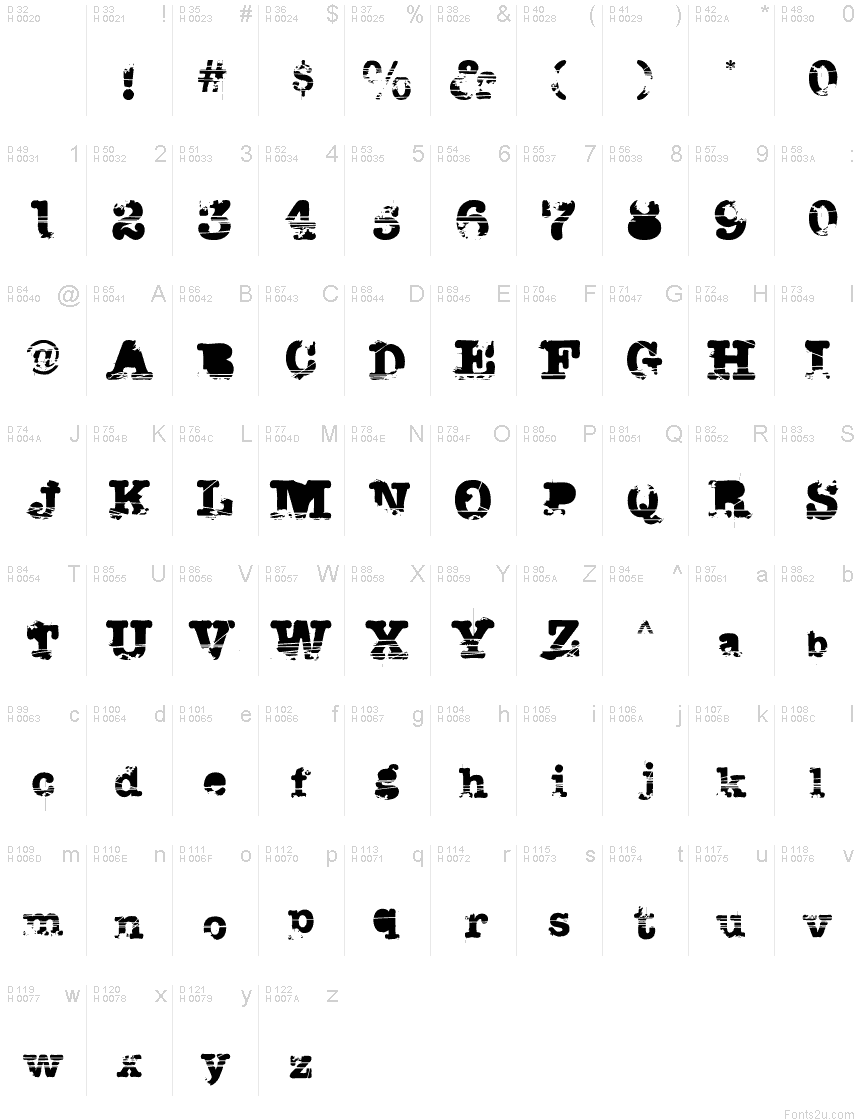
Sacrafical è un font display gratuito dallo stile eroso, che richiama l'estetica usurata dei vecchi caratteri in legno. Con le sue grazie arrotondate e massicce e i contorni irregolari, l'alfabeto appare grande, crudo e segnato dal tempo. La presenza ricorrente di tagli orizzontali conferisce ai caratteri un aspetto graffiato, stampato e leggermente instabile.
Questo lo rende perfetto per titoli di poster, grafiche per album dallo stile cupo, volantini horror, design streetwear e cartelli dove la texture danneggiata comunica forza visiva. Essendo un font gratuito, funziona alla grande anche per testi brevi e parole d'effetto, specialmente se cerchi forme corpose dal sapore vintage con quel look tipico della stampa rovinata.